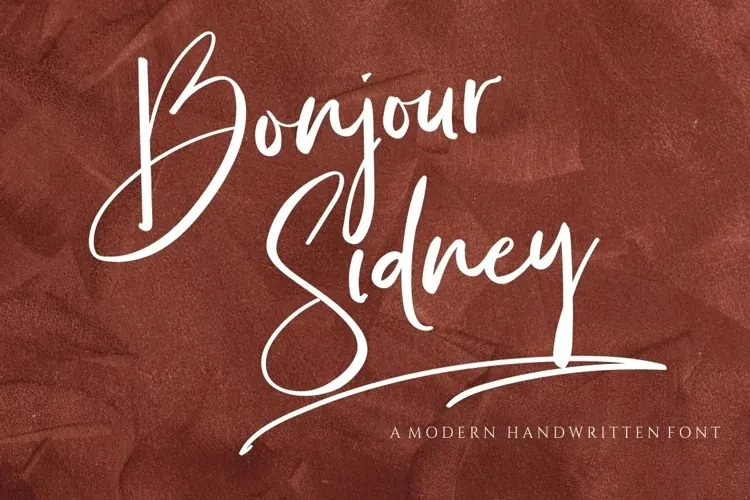
Bonjour Sydney Font – Download Grátis
A fonte ‘Bonjour Sydney Font’ é perfeita para qualquer projeto que exija uma tipografia elegante e vibrante. Embora não seja um tipo de letra formal ou elaborado, ela oferece um toque de originalidade e personalização que se adapta a vários ambientes de uso. Seja em logotipos, materiais de marca, cartazes de eventos, embalagens de presentes ou postagens nas redes sociais, esta fonte traz ao seu design uma sensação leve e moderna que combina bem com qualquer estilo. Com sua gama de formas fluidas e linhas levemente onduladas, a ‘Bonjour Sydney Font’ é o tipo de recurso gráfico indispensável para designers em busca de um toque único e divertido. Sem dúvida, ela está destinada a tornar seu trabalho mais vistoso e memorável.